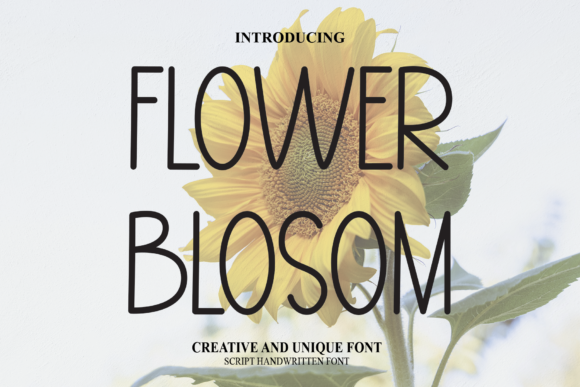
Flower Blosom
Flower Blosomのような高品質の素材をお探しの場合、このプレミアムパッケージはクリエイティブなプロジェクトに素晴らしい選択です。
POD(オンデマンド印刷)製品、結婚式の招待状、またはソーシャルメディアのグラフィックを作成している場合でも、Flower Blosomは理想的です。